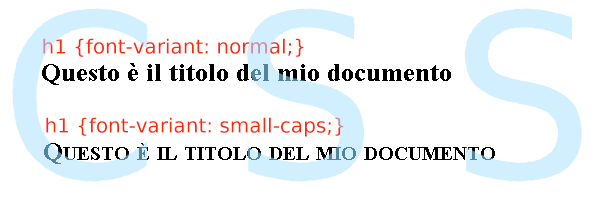
Guida CSS, il maiuscoletto con font-variant
Proseguiamo con questa guida ad analizzare gli aspetti della formattazione del testo attraverso i fogli di stile CSS. In particolare vedremo come sia possibile utilizzare la proprietà font-variant per applicare ad un selettore l’effetto “maiuscoletto”.
Il maiuscoletto nei CSS
Il tipografia il maiuscoletto è una particolare rappresentazione del testo usata con finalità grafiche o per migliorare la leggibilità delle parole. Nel maiuscoletto i caratteri maiuscoli sono rappresentati con la relativa lettera maiuscola mentre i caratteri minuscoli vengono rappresentati con le corrispondenti lettere maiuscole ridotte però in altezza. Nell’immagine che apre questo post è possibile osservare lo stesso testo scritto convenzionalmente ed in maiuscoletto.
L’effetto maiuscoletto è supportato da molti programmi di videoscrittura (come OpenOffice Writer) ma può essere facilmente implementato anche nei fogli di stile CSS associati ad una pagina web.
La proprietà font-variant in CSS
Come abbiamo già accennato il maiuscoletto in CSS è associato alla proprietà font-variant e si applica tipicamente ai selettori HTML che individuano elementi di testo o blocchi. Osserviamo un breve estratto di codice:
h1 {
font-variant: small-caps;
}
La proprietà font-variant può assumere solo due valori:
• normal: è il valore predefinito e lascia il testo nel suo aspetto normale. Può essere omesso a meno che nel contesto gerarchico del foglio di stile non occorra forzare la visualizzazione normale del testo.
• small-caps: indica al browser di rappresentare il testo in maiuscoletto.
La maggior parte dei browser recenti gestiscono correttamente il valore small-caps della proprietà font-variant. Nei browser che non supportano questa indicazione ed in quelli che non gestiscono i fogli di stile il testo verrà rappresentato nella sua forma normale.